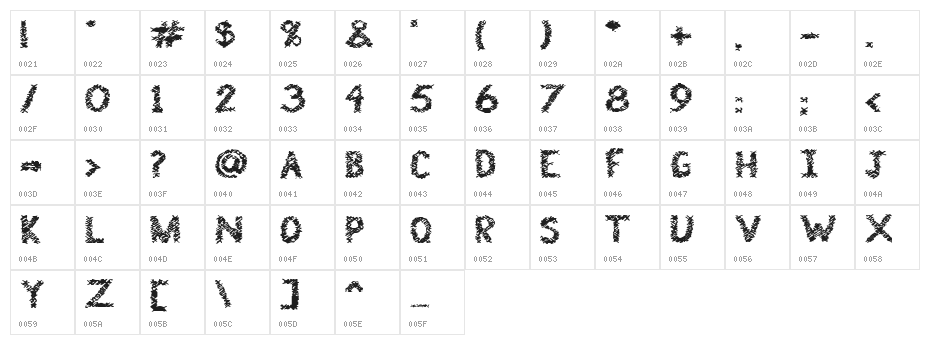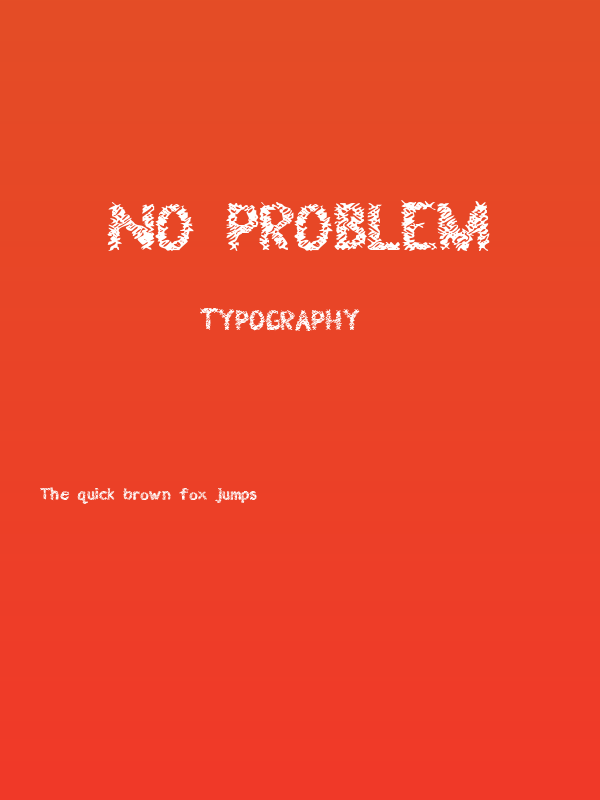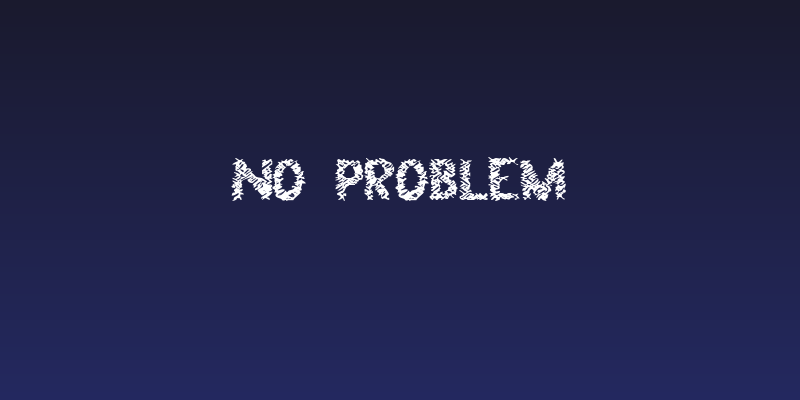
No Problem Font
✎ Broken
| Vorgeschlagene Projekte | Ideal for eye-catching posters, album covers, or branding that requires a unique and artistic flair. |